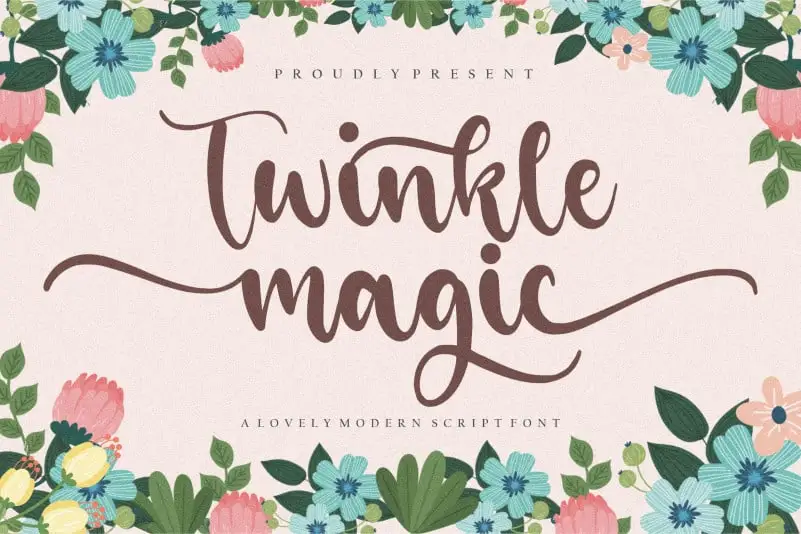
Twinkle Magic Script Font – Fonte Grátis
Twinkle Magic Script Font
A Twinkle Magic Script Font é perfeitamente adaptada para diversas aplicações digitais, seja para embalagens de produtos, criação de marca, revistas, mídias sociais ou até mesmo decorar um texto para destacá-lo acima de um fundo. Sua caligrafia espontânea e colorida é atraente e única, tornando-a uma escolha excepcional não apenas para aplicações gráficas tradicionais como cartões de aniversário ou cerimônias especiais, mas também para trabalhos mais modernos em redes sociais e designs digitais. Como parte da categorização ‘Handwritten Fonts’ criada pelo designer balpirick, a Twinkle Magic captura o espírito encantador e vibrante que as letras manuscritas podem transmitir, permitindo-lhe criar texturas e estilos inovadores. Seja para decorar seu blog ou site pessoal, ou para um projeto de publicidade grandioso, essa fonte é uma ótima opção.